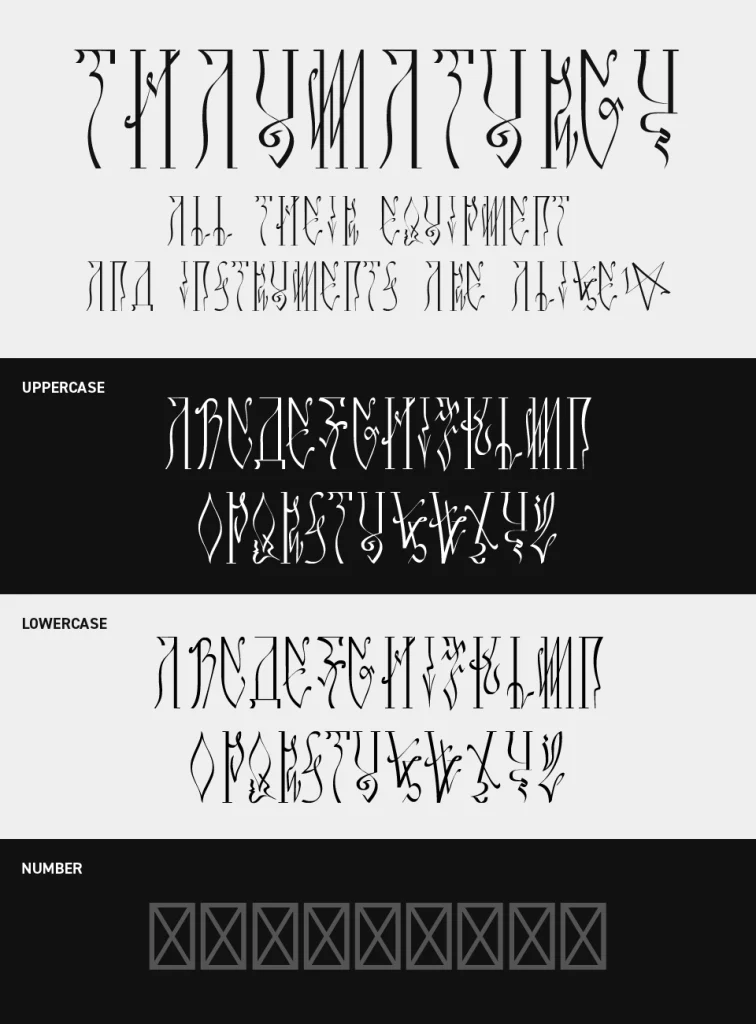
Thaumaturgy Font
Thaumaturgyフォントは、極端に細長い字形と有機的にうねる装飾が印象的な、呪術的で幻想世界を感じさせるアートフォントです。
一般的なタイポグラフィから大きく逸脱した造形が独特で、一目見ただけで異世界の空気感を生み出します。
文字の一部が植物の蔓や魔法陣のように絡み合い、神秘性や妖しさを強く演出しています。ダークファンタジー、魔術書、ゴシック作品、世界観重視のゲームタイトルなど、物語性やミステリアスな演出を表現したい場面で映えるフォントです。
収録文字は、大文字の収録となっています。